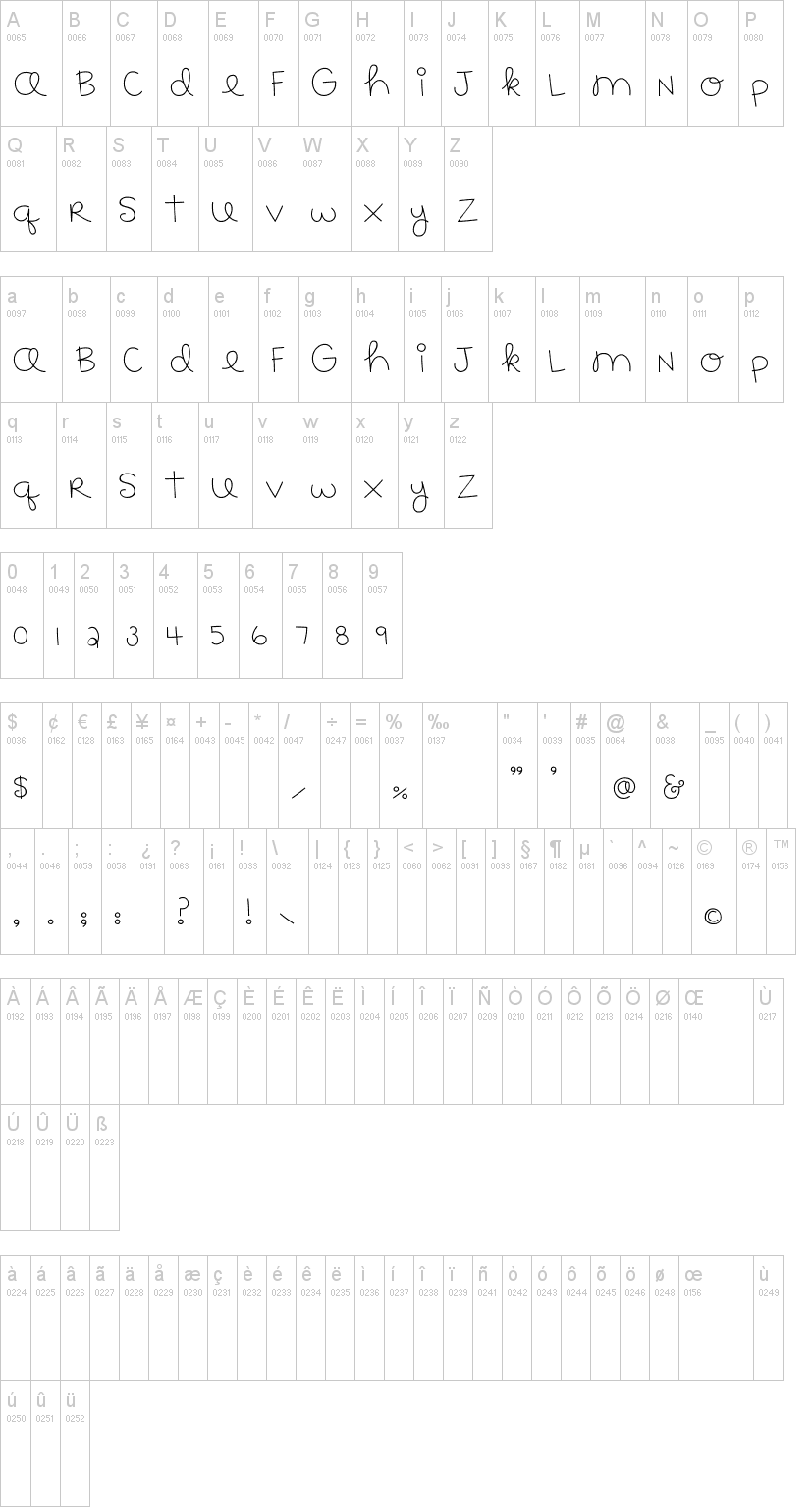
MTF 183 字体是一款美式英文字体,它由MTF字体库推出,是一款斜体字体,具有优雅、精致、活泼的外观特点。它的字形清晰,字符间距舒适,比较适合用于报刊、书籍、海报、商业广告等设计领域。内容介绍
MTF 183是一款非常不错的手写艺术字体,具有很好的视觉感,适合于文化类的宣传设计、商业类品牌的广告和产品包装设计以及个性化文字排版等较多场景。